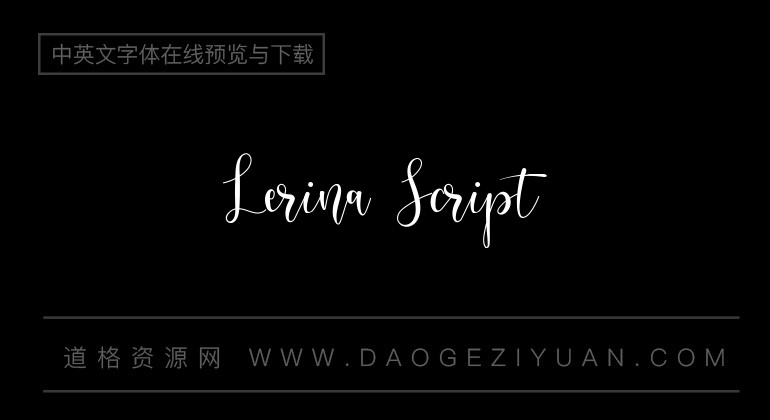
Lerina Script
Lerina Script 是一种手写风格的字体,它具有非常自然、流畅和优雅的笔画,适合用于个人和商业项目。该字体由马来西亚的设计师Muhadi创建,它的特点是在字母间和笔画末尾添加了一些装饰性的线条和笔画,这些线条和笔画让 Lerina Script 更显独特和优美。 Lerina Script 提供了多种字形和连字,可以满足不同风格的设计需求,比如手写信件、海报、包装、徽标和品牌等。该字体提供了 OTF、TTF 和 WOFF 格式的文件,可以在各种设计软件中使用,包括 Photoshop、Illustrator、InDesign 等。
Lerina Script是一款非常不错的手写艺术字体,具有很好的视觉感,适合于文化类的宣传设计、商业类品牌的广告和产品包装设计以及个性化文字排版等较多场景。